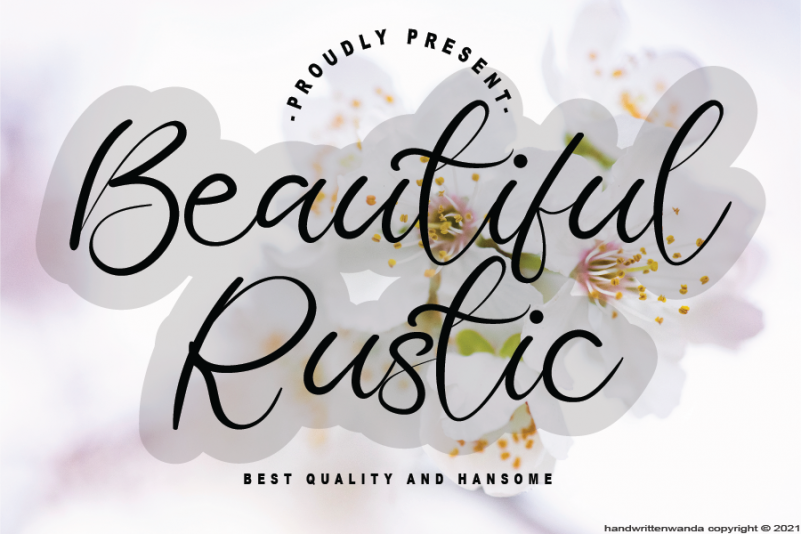
Beautiful Rustic Font – Download Grátis
Esta é uma fonte escrita a mão que combina suavidade com versatilidade, adequada para projetos variados. Ela tem um toque quente e quirk, ao mesmo tempo alegre e descontraído, tornando qualquer projeto realista de arte. Este é um excelente parceiro para designers ativos, especialmente aqueles que valorizam uma fonte escrita a mão. Trazem esta bela fonte com você e explora suas infinitas variações em cada trabalho que você faz. Aprenda novos truques e crie artes únicas e personalizadas sem limites. Experimente essa fonte agora e veja o quanto ela pode expandir seus horizontes de design.
Designer: handwrittenwanda